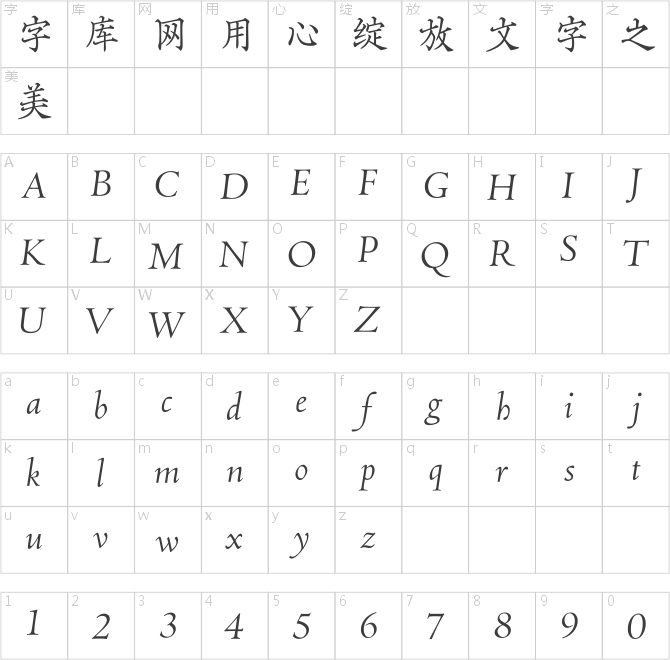
字體名稱: 方正志安體
方正志安體
方正志安體介紹
方正志安體是日本首次登陸的一款元朝體,是一款組合字體,漢字部分源自元代福建刊本《分類補注李太白詩》的“志安體”,西文部分為「K.E.Libra」,組合成為具有現代感的綜合書體。 可以應用于文本裝潢、信息展示、網頁設計、篆刻制模、數據制作、裝潢設計、計算藝術設計、視覺設計、字帖等領域。